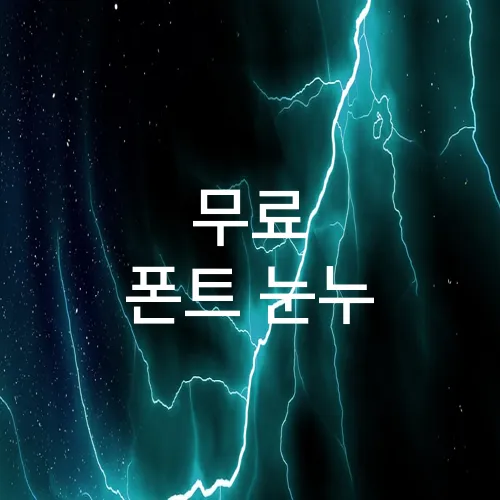
1. 무료 폰트 눈누의 숨겨진 보석: 당신의 디자인을 변화시킬 수 있는 선택
숨은 보석, 무료 폰트 눈누의 다양성
무료 폰트 눈누는 다양한 디자인의 변화를 원하는 사람들에게 숨겨진 보석과도 같습니다. 여기에는 광범위한 종류의 폰트가 제공되어 어떤 프로젝트든지 감각적이고 특별하게 만들 수 있는 장점이 있습니다. 특히 한국적인 감성을 강조하는 ‘둥근모꼴’ 폰트는 일러스트나 그래픽 디자인에서 빈번하게 사용됩니다.
– 둥근모꼴: 부드럽고 개성 있는 라인으로 광고 및 콘텐츠에 활력을 불어넣습니다.
– 남산체: 명료하면서도 전통성이 느껴지는 글자로, 웹사이트에서 자주 활용됩니다.
효율적인 선택, 디자인 필수 아이템
디자인을 효과적으로 돋보이게 만드는 데 있어 중요한 것은 정확한 폰트 선택입니다. 무료 폰트 눈누는 아름다움과 기능성을 모두 고려한 옵션을 제공합니다. ‘조선체’는 클래식한 분위기를 연출하는 데 유용하고, ‘잔디체’는 귀엽고 독특한 감성을 자아내어 인패션이나 블로그에 적합합니다.
– 조선체: 정갈하고 전통적인 느낌을 주며, 교육자료에 적합합니다.
– 잔디체: 개성 넘치는 스타일로 캐릭터 상품이나 키치한 디자인에 이상적입니다.
세련된 디자인을 위한 필수 도구
디자인 트렌드는 빠르게 변하고 있지만, 무료 폰트 눈누의 기본적인 매력은 변하지 않습니다. 특히, 각 폰트의 활용사례와 사용자 리뷰를 참조하면 보다 효과적인 선택이 가능합니다. ‘나눔바른펜’ 폰트는 필기체 스타일의 자연스러움으로 서적 디자인이나 노트에 자주 사용됩니다.
– 나눔바른펜: 따뜻하고 부드러운 필기 스타일로 감성적인 분위기에 적합합니다.
– 배달의민족체: 트렌디한 느낌을 살려 현대적인 브랜드에 잘 매치됩니다.
이처럼 무료 폰트 눈누는 다양한 디자인적 요구에 대응하는 다채로운 옵션을 제공하여, 누구나 무료로 창의적이고 수준 높은 작업을 할 수 있도록 지원합니다. 이러한 폰트 선택은 결국 사용자들의 창작을 더욱 빛나게 하고, 당신의 디자인을 한층 더 다채롭게 변화시킵니다.
2. 인기 상승 중인 힙한 폰트: 2023년 디자인 트렌드를 이끌다
2023년 주목받는 디자인 트렌드: 힙한 무료 폰트
최근 ‘무료 폰트 눈누’에서 제공하는 폰트들이 디자이너들 사이에서 큰 인기를 끌고 있습니다. 특히 2023년은 개성 있는 디자인을 중요시하게 되었으며, 이를 반영한 힙한 폰트들이 주목받고 있습니다. 사람들은 이제 단순한 타이포그래피를 넘어 독특함과 창의성을 가진 폰트를 찾고 있습니다.
– 에스페란토: 깔끔하면서도 현대적인 느낌으로, 모던한 프로젝트에 적합합니다.
– 눅스: 이 폰트는 좀 더 예술적이고 실험적인 프로젝트를 위해 설계되었습니다.
이 두 무료 폰트는 현재 많은 브랜드와 디자이너들 사이에서 트렌디하게 사용되고 있으며, 웹사이트뿐만 아니라 인쇄 매체에서도 광범위하게 활용되고 있습니다.
폰트가 디자인을 좌우한다
오늘날의 디자인에서는 폰트 하나로 전체 분위기를 좌우할 수 있습니다. 무료 폰트 눈누에서 제공하는 독창적인 폰트들은 브랜드 아이덴티티를 강조하는 데 필수적입니다. 최근 출시된 ‘Eulyoo 123’ 폰트는 한글 디자인에 적합합니다.
– 깔끔한 인상: 가독성이 높아 모든 연령층에서 사용하기 좋습니다.
– 다양한 굵기와 스타일: 여러 디자인에 용이하게 사용 가능합니다.
이와 같은 특성 덕분에 다양한 분야에서 활용되고 있으며, 폰트를 이용해 별도의 디자인 소스 없이도 독특한 인상을 줄 수 있습니다.
더 많은 선택, 더 많은 가능성
디자이너들은 언제나 새로운 소재와 작업 방식을 추구합니다. 이와 같은 요구를 충족하기 위해 ‘무료 폰트 눈누’는 끊임없이 업데이트되며, 전 세계 여러 디자이너들이 자유롭게 활용할 수 있는 자원을 제공합니다.
– 최신 트렌드 반영: 다양한 선택지를 통해 최신 트렌드를 주도할 수 있습니다.
이러한 자세한 폰트 선택 옵션들 덕분에, 디자이너들은 자신만의 독창적인 디자인 작품을 창출할 수 있게 됩니다. ‘무료 폰트 눈누’는 항상 새로운 아이디어를 탐색하는 도구로서 그 가치를 더해가고 있습니다.
3. 눈누에서 찾은 독특한 서체: 개성과 창의성을 더하다
눈누에서 빛나는 독특한 서체
무료 폰트 플랫폼인 눈누는 디자이너와 창작자들에게 필수적인 도구로 자리 잡았습니다. 이곳에서는 다양한 무료 폰트를 손쉽게 다운로드할 수 있는데요, 그 중에서도 특별히 독특한 서체들이 있습니다. 이런 폰트들은 개성과 창의성을 필요로 하는 프로젝트에서 매우 유용하게 사용됩니다.
– 대한체: 대한체는 대한민국의 전통과 문화를 현대적으로 재해석한 서체입니다. 과거와 현재의 만남을 시각적으로 표현하여, 역사적인 느낌을 살리면서도 트렌디한 디자인을 완성할 수 있습니다.
– 한글날체: 이 서체는 한글날을 기념하여 제작된 서체로, 한글의 미학적 요소를 강조합니다. 포스터나 이벤트 배너 등에서 한글의 아름다움을 돋보이게 할 때 적합합니다.
창의적 프로젝트에 어울리는 선택
독창적인 디자인을 원하시는 분들께는 눈누에서 제공하는 특정 서체들이 특히 추천됩니다. 예를 들어, 감각적인 느낌을 강조하고 싶을 때는 ‘배민 한나체’를 사용할 수 있습니다. 배달의민족에서 제공하는 이 폰트는 세련되고 경쾌한 느낌으로 많은 디자이너로부터 호평을 받고 있습니다.
– 빙그레체: 빙그레에서 제공하는 이 서체는 간결하면서도 개성 있는 표현이 가능합니다. 주로 젊고 활기찬 브랜드에서 활용되고 있습니다.
이와 같이 눈누에서 제공하는 무료 폰트들은 프로젝트의 성격에 따라 알맞게 선택할 수 있으며, 창의적인 컴포지션을 완성하는 데 많은 도움이 됩니다.
4. 무료 폰트 눈누와 함께하는 실용적이고 경제적인 디자인 솔루션
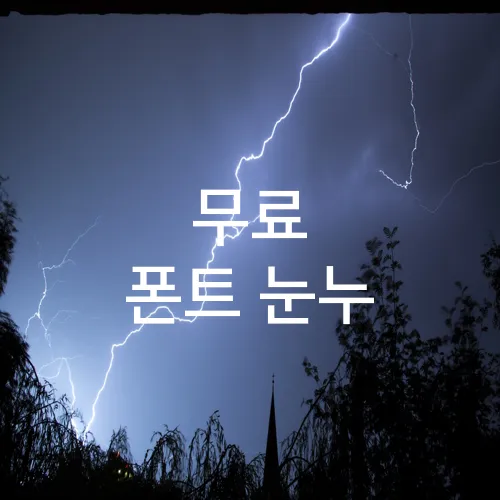
실용적이고 경제적인 무료 폰트 플랫폼
무료 폰트 눈누는 다양한 무료 폰트를 제공합니다. 이는 예산이 제한된 스타트업이나 소규모 디자인 스튜디오에 적합합니다. 적은 비용으로도 전문성을 살린 디자인을 구현할 수 있기 때문에 활용도가 높습니다.
대표적으로 ‘눈누’에서 제공하는 폰트 중 ‘배달의민족 주아체’, ‘에스코어 드림’, ‘제주고딕’ 등은 인기 있는 선택입니다. 이러한 폰트들은 브랜드 아이덴티티를 강화하면서도 디자인 비용 절감에 효과적입니다.
– 배달의민족 주아체: 독특하면서도 깔끔한 이미지로 인식되었습니다.
– 에스코어 드림: 가독성이 좋아 모바일 앱이나 웹사이트에 적합합니다.
– 제주고딕: 절제된 느낌으로 다양한 디자인 프로젝트에 적용됩니다.
디자인 효율성을 높여주는 무료 폰트 활용
무료 폰트 눈누를 활용하면 프로젝트마다 새로운 폰트를 구매하는 대신, 원하는 스타일의 폰트를 손쉽게 찾을 수 있습니다. 이로 인해 디자인 작업 시간을 줄이고 효율성을 높일 수 있습니다.
디자인 작업 중 변경해야 하는 요소가 많지만 빠른 수정이 가능한 환경을 제공합니다. 다양한 스타일을 비교하면서 가장 적합한 폰트를 선택하는 것이 가능해집니다.
– 시간 절약: 다양한 폰트를 한곳에서 즉시 다운로드 가능
– 경제적: 무료 라이선스로 추가 비용 없음
다양한 디자인 프로젝트에서의 활용 사례
기업 프레젠테이션, 온라인 마케팅 캠페인, 소셜 미디어 콘텐츠 제작에도 무료 폰트 눈누는 유용합니다. 특히, 비영리 조직이나 개인 블로그에서 예산을 절약하면서도 고품질의 비주얼 컨텐츠를 제작할 수 있는 기회를 제공합니다.
– 온라인 캠페인: 독창적인 폰트를 활용하여 더 많은 참여 유도
– 교육 자료: 가독성이 좋은 폰트로 학습 효과 극대화
무료 폰트 눈누를 활용하여 다양한 디자인 솔루션을 찾아보세요. 공식 사이트에서는 각각의 폰트에 대한 라이선스 정보를 제공하므로, 사용 전 반드시 확인하는 것이 중요합니다. 디자인의 품질을 높이면서도 경제적인 해결책을 찾고자 한다면 꼭 검토해 보시기 바랍니다.
5. 영화와 팝 문화에서 영감을 받은 획기적인 폰트 스타일
영화와 팝 문화의 매력적 영감을 담은 폰트
무료 폰트 눈누에서 제공하는 다양한 폰트 중 영화와 팝 문화에서 영감을 받은 획기적인 폰트 스타일이 최근 많은 주목을 받고 있습니다. 예를 들어, ‘Star Jedi’ 폰트는 스타워즈의 특유의 서체를 연상시키며, 영화 팬들에게 인기를 끌고 있습니다. 이러한 폰트는 팬 아트나 관련 이벤트 포스터에 활용하기 적합하여, 많은 디자이너들이 선호하는 스타일입니다.
또한, ‘Avengers’ 스타일의 폰트도 빼 놓을 수 없습니다. 이 폰트는 마블의 대표적인 로고 스타일을 재현하여 팝 컬처 팬들에게 큰 사랑을 받고 있습니다. 이러한 폰트를 사용하면 다양한 프로젝트에 유니크한 감각을 더할 수 있습니다.
– 스타워즈 테마: ‘Star Jedi’
– 마블 테마: ‘Avengers’
– 다양성: 한글과 영어, 그 외의 문자 스타일을 아울러 제공
이러한 강점으로 무료 폰트 눈누는 사용자들 사이에서 높은 인기를 끌고 있습니다.
무료 폰트 눈누로 무한한 창작 가능성 실현
눈누 폰트는 매달 새로운 폰트를 추가함으로써 사용자에게 지속적인 유용함을 제공합니다. 또한, 최신 트렌드와 철저한 품질 검토를 거쳐 업데이트되며, 사용자 피드백을 항상 반영합니다.
디자인 초보자부터 전문가까지, 무료 폰트 눈누는 누구나 쉽게 접근할 수 있는 플랫폼으로, 앞으로도 디자인 작업에 없어서는 안 될 파트너로 자리잡을 것입니다. 다양한 무료 폰트를 통해 여러분의 창작물을 더욱 빛나게 하세요.
이와 같은 기능과 서비스로 무료 폰트 눈누는 디자이너에게 무한한 가능성을 제공합니다. 여러분의 작업에 더한층 창의력을 불어넣을 준비가 되어 있습니다.